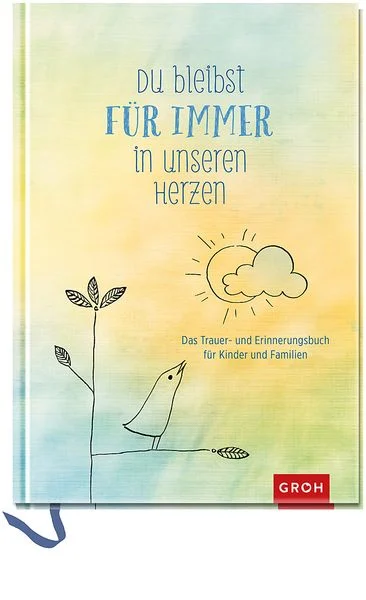
Fröhliche, Trauerschriftart gesucht
Servus. Ein Kunde hätte gerne diese Schriftart (o.ä.). Vielleicht kann mir da jemand weiterhelfen, bevor ich anfange von Hand zu gestalten!? Vielen Dank.